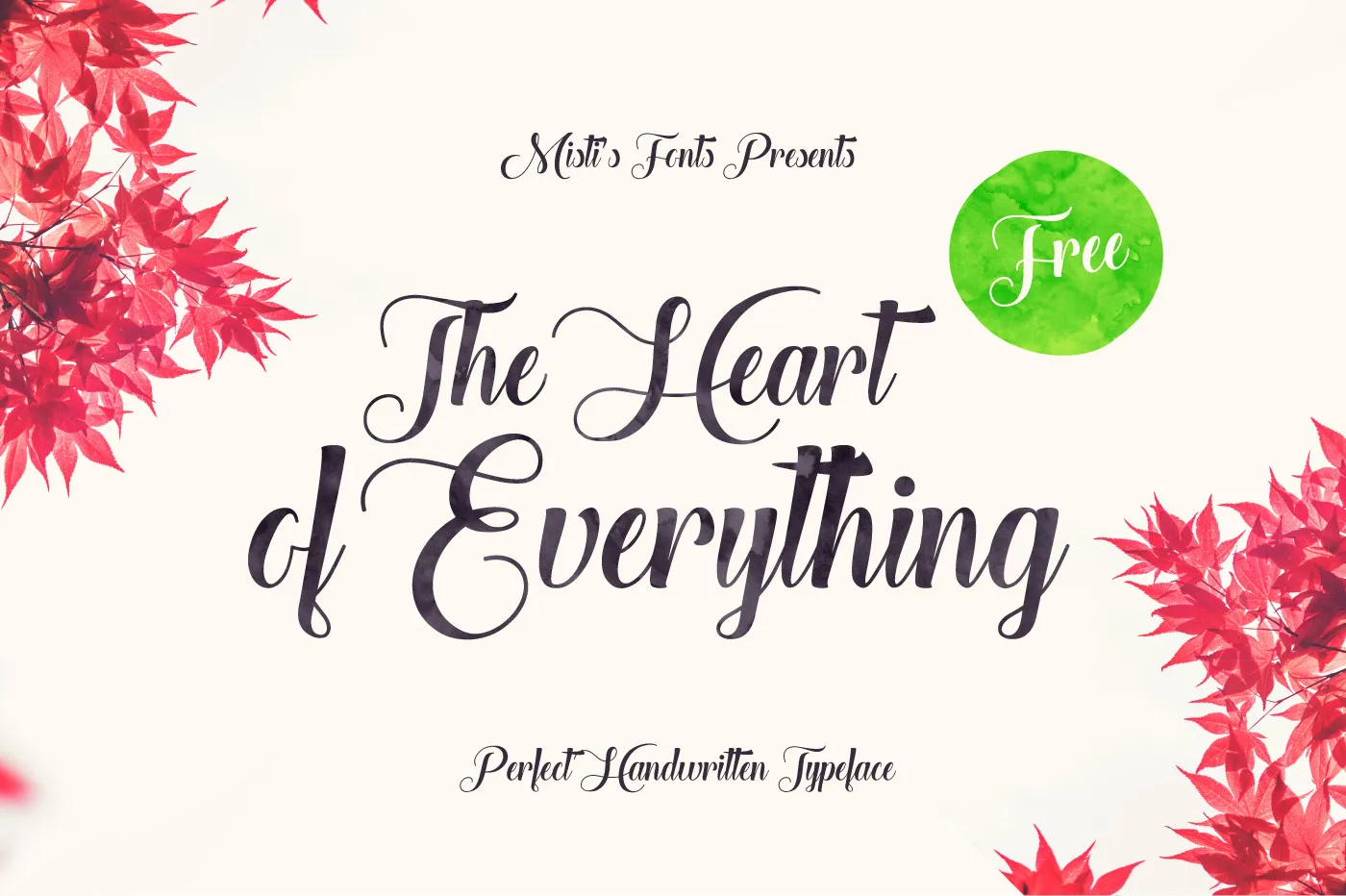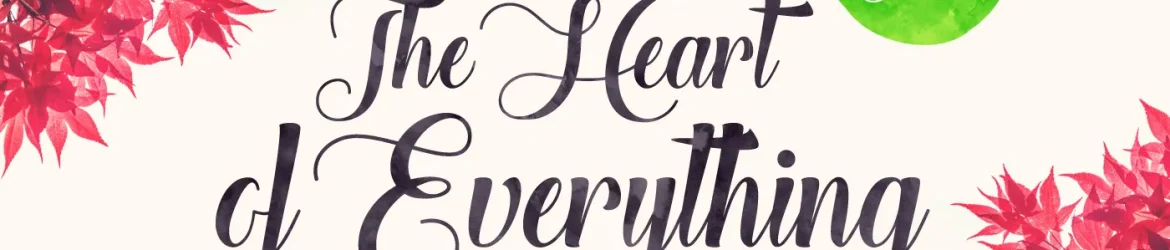
The Heart of Everything Font – Download Grátis
Aqui está uma descrição envolvente e natural para a página de download da fonte ‘The Heart of Everything Font’, no estilo que solicitei: Vamos lhe dar um presente extra hoje com uma elegante fonte curva e escrita à mão, perfeitamente criada pela Misti’s Fonts. Eu preparei todos os imagens de pré-viés para mostrar a potencial dessa fonte de grão de café que você não pode perder. A fonte é gratuita tanto para uso pessoal quanto para caridade. Para um uso comercial, contate diretamente a Misti’s Fonts. Isso certamente será o toque final em seu projeto e dará ao texto um toque único e encantador. Não perca essa oportunidade de enriquecer seu design com algo tão especial e gratuito.